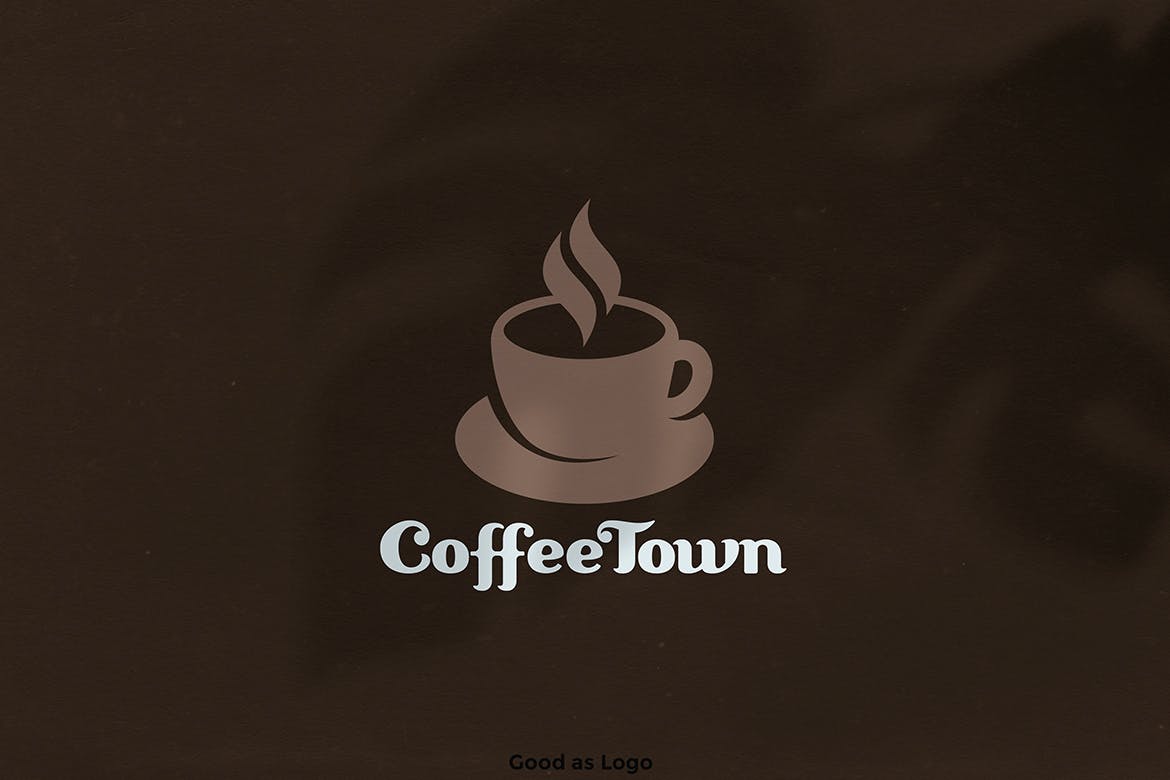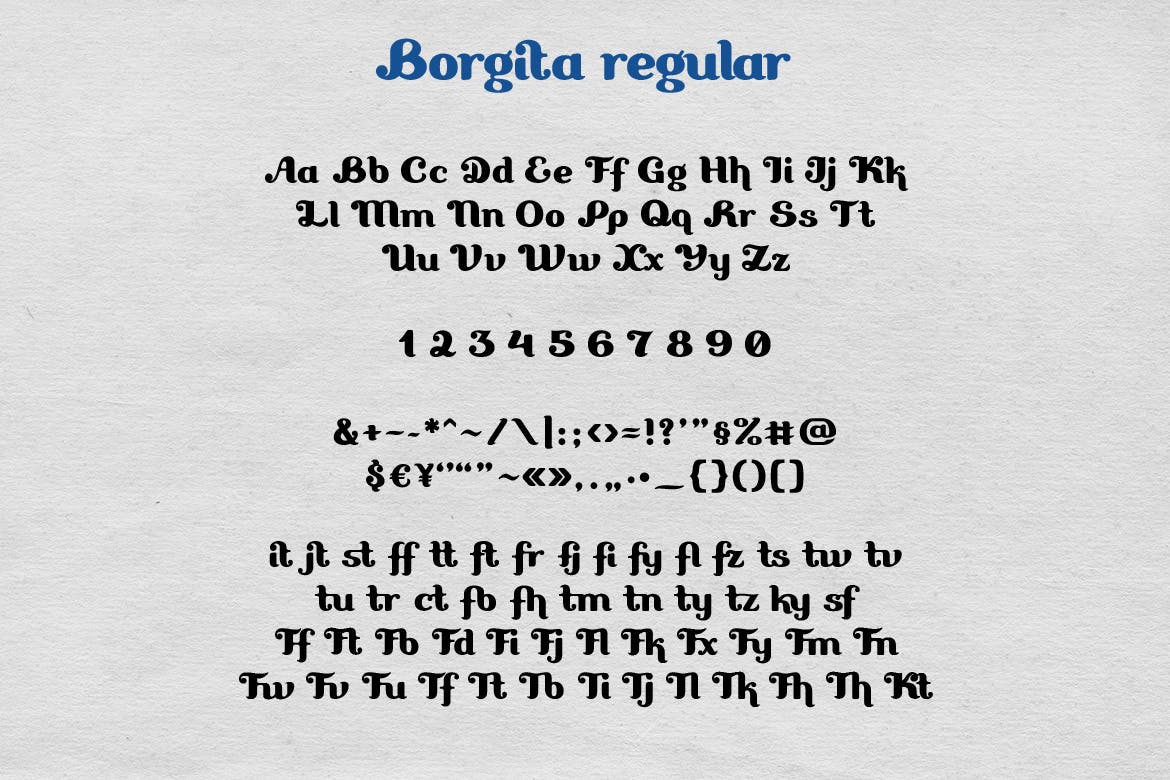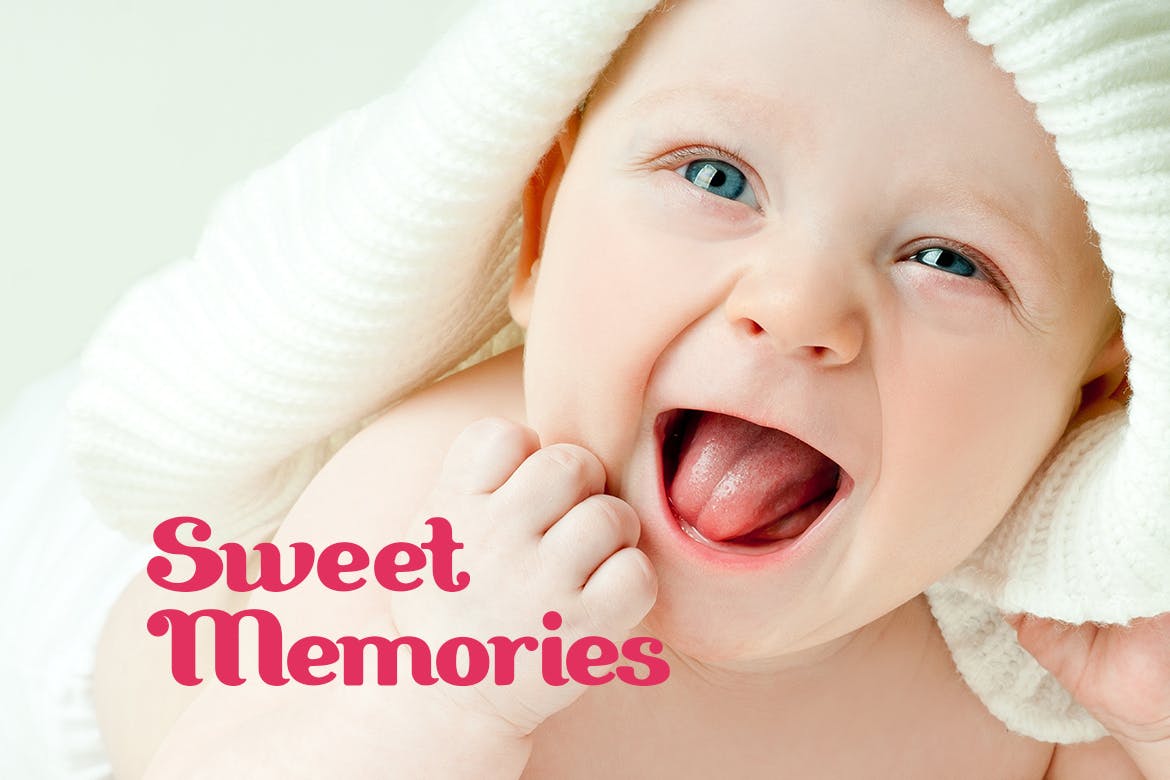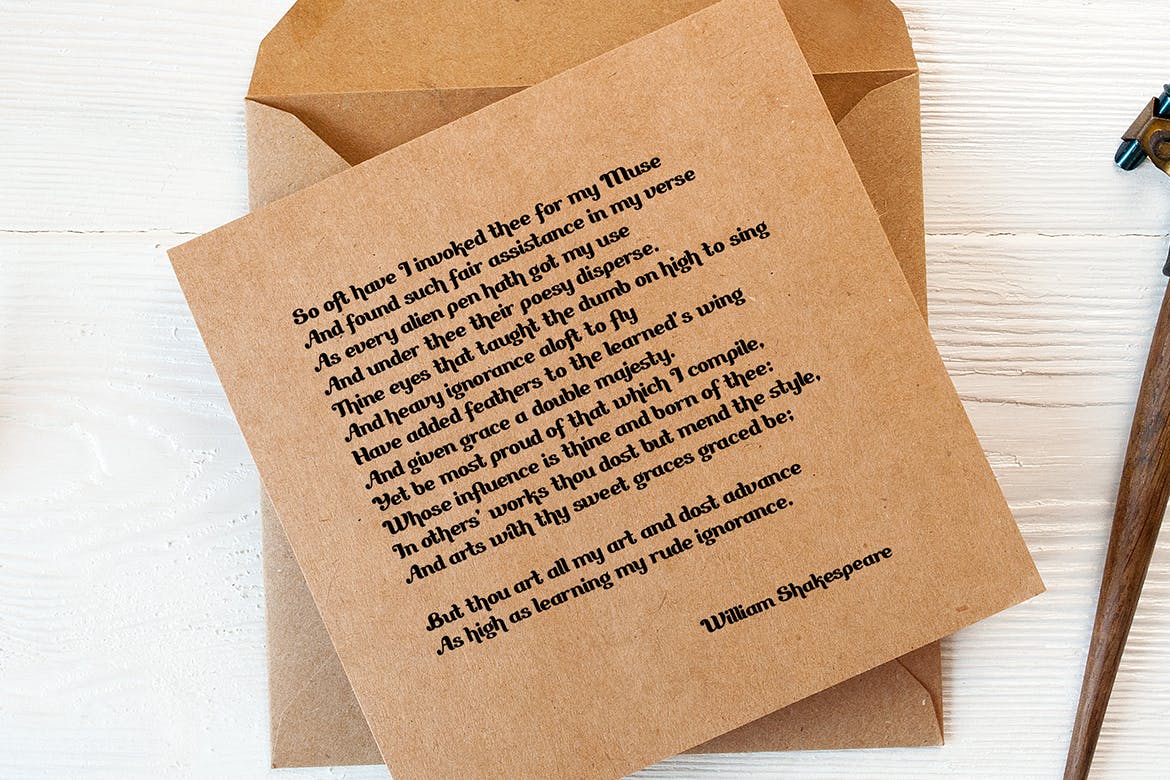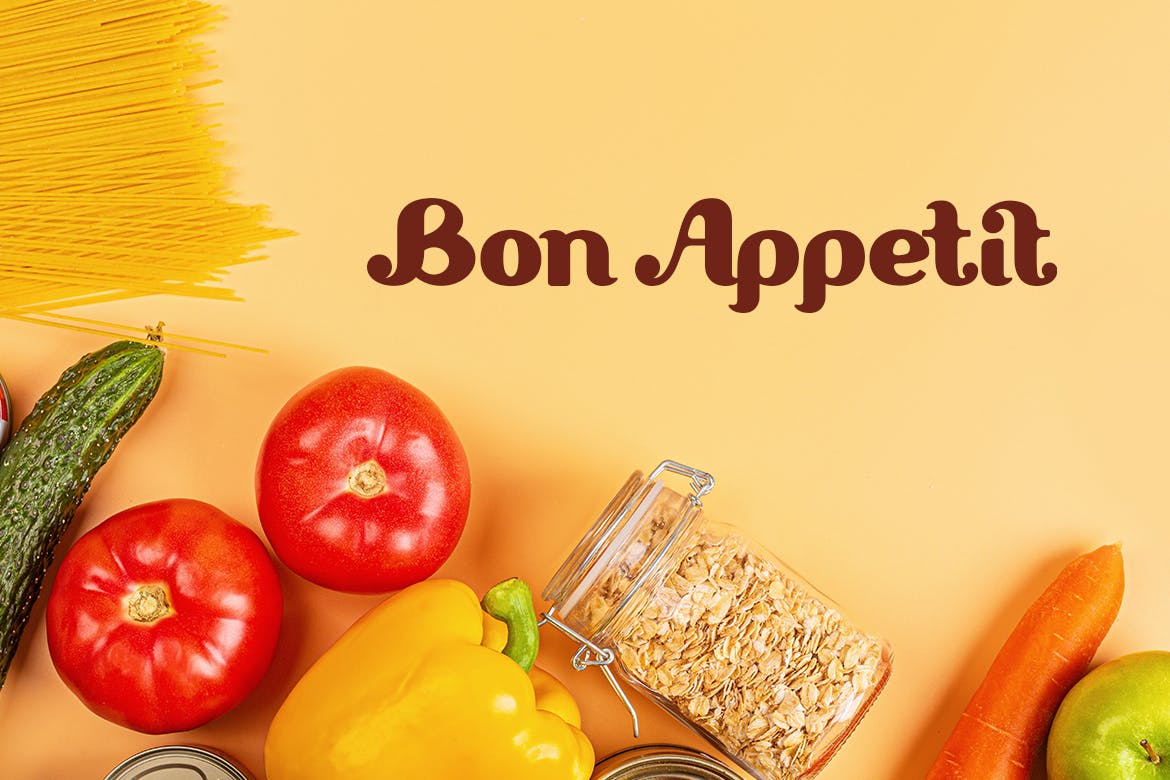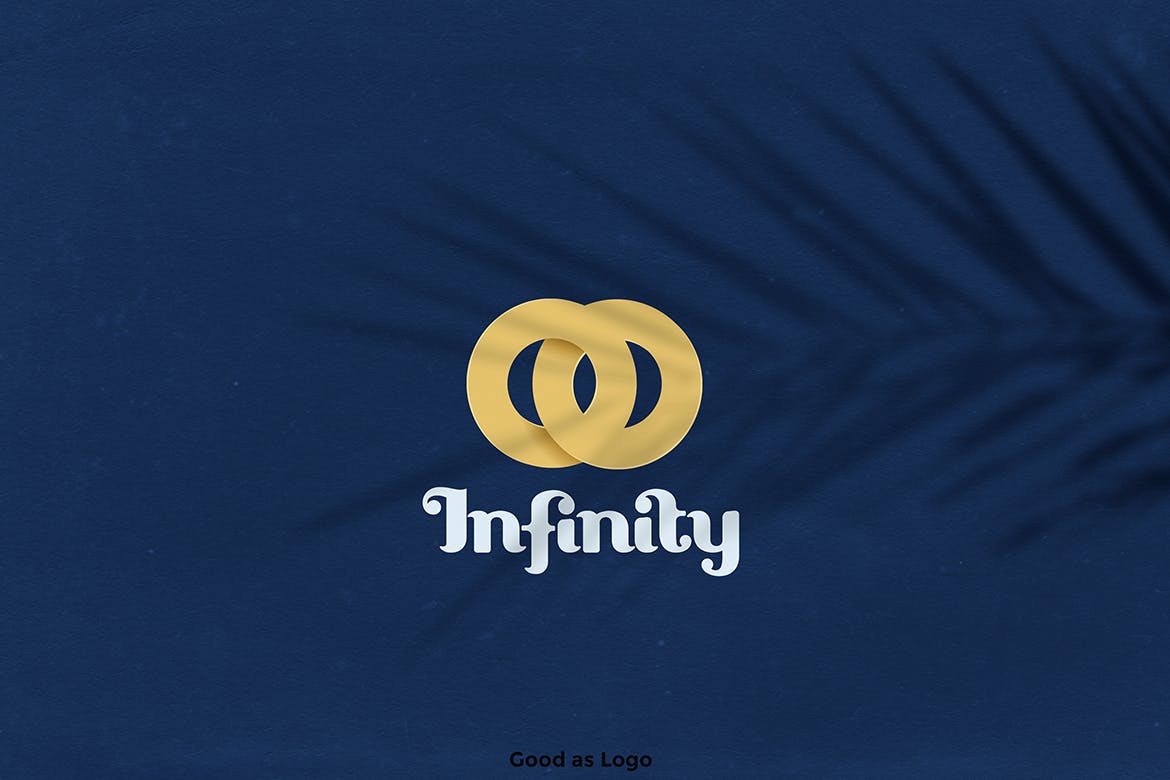
دانلود فونت خطاطی بورجیتا برای طراحی‌های زیبا
Borgita Script Calligraphic Font
فونت بورجیتا، انتخابی عالی برای لوگوها و طراحی‌های خاص شما.
فونت بورجیتا یک فونت خطاطی زیبا و مدرن است که به منظور ایجاد لوگوها و ترکیب‌های جذاب طراحی شده است.